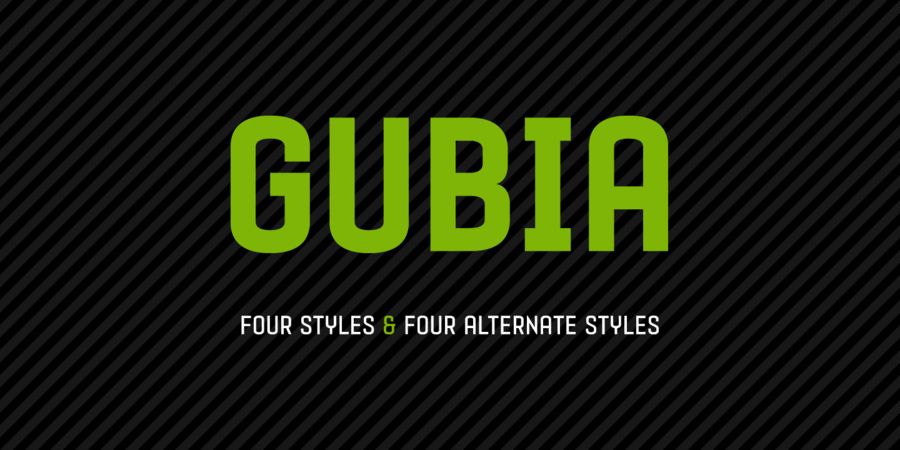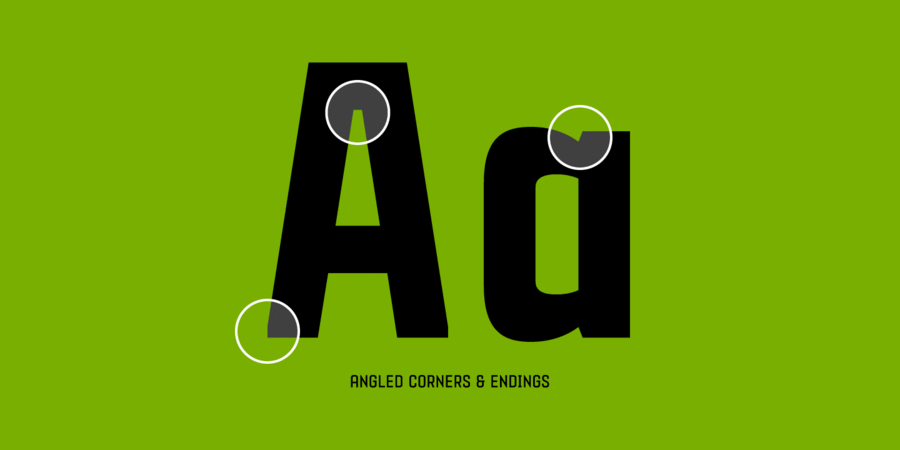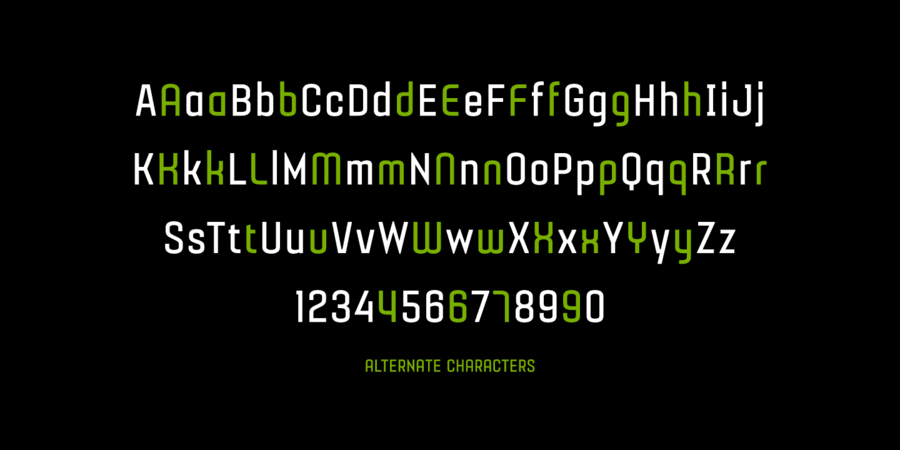
Gubia (8 шрифтів)
8 накреслень
Опис гарнітури GubiaGubia – це геометричний шрифт без засічок зі стиснутими пропорціями. Він найбільш придатний для заголовків будь-яких розмірів, а також для коротких і середньої довжини текстових блоків. Стандартні накреслення надають текстам класичного вигляду, тоді як альтернативні додають їм грайливості. Gubia складається з 8 накреслень, 4 насиченості з 4 альтернативами, кожне з яких містить капітель і набір гліфів для кількох мов. Шрифт розробив Пабло Балселлс у 2014 році.
Асоціації з сімейством шрифтів GubiaОсобистість і характер гарнітури:
неоновий, точний, футуристичний, рівний, тонкий, статичний, логічний, холодний, легкий, міський, сучасний, інженерний, урбаністичний, креслярський, скляний, прозорий, дротяний, спокійний, худий, якісний, західний, машинний, стійкий, космічний, чіткий, стабільний, твердий, серйозний, надійний, впевнений, техногенний, практичний, прагматичний, технічний, міцний, переконливий, сильний, індустріальний, крутий, амбітний, суворий, важкий, гучний, важливий, сталевий, залізний, лаконічний, мінімалістичний, модний, комфортний, ясний, чистий, невагомий, гладенький, крихкий, автоматичний, елементарний, гнучкий, комп'ютерний, глобалізований, глобалістічний, зрозумілий, доступний, спортивний, потужний, авторитетний, помітний, залізничний, прямокутний, промисловий
фантастика, гаджет, девайс, креслення, архітектура, інженер, Місто, електроніка, прилад, айтішник, айті, IT, технології, космос, дизайн, техніка, конструктор, автоматика, гра, авто, ремонт, залізо, промисловість, верстат, інструмент, електростанція, енергетика, завод, тренажери, паливо, кіно, Футбол, комп'ютерна гра, нафта, селфі, кінотеатр, чистота, інновації, наука, астрономія, небо, вода, урбаністика, транспорт, комп'ютер, інтернет, мобільний зв'язок, метро, ліки, медицина, математика, автомобіль, автобус, коворкінг, кіберспорт, спорт, машинобудування, мотор, двигун, шоу, телебачення, залізниця, іграшка, зореліт, розваги, атракціон, андроїд, робот Гарнітура асоціюється з віком: